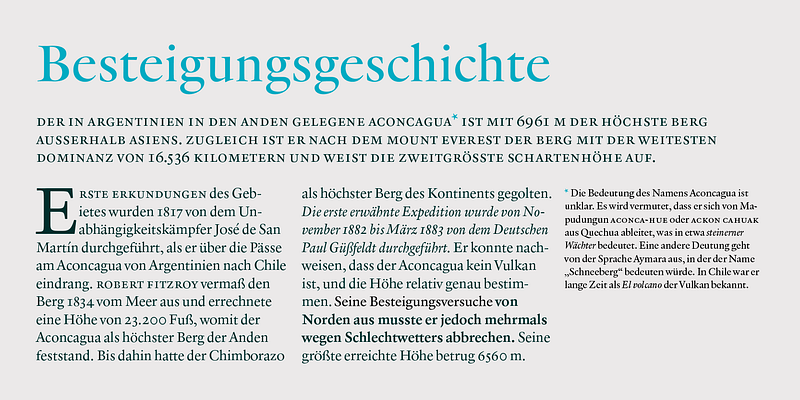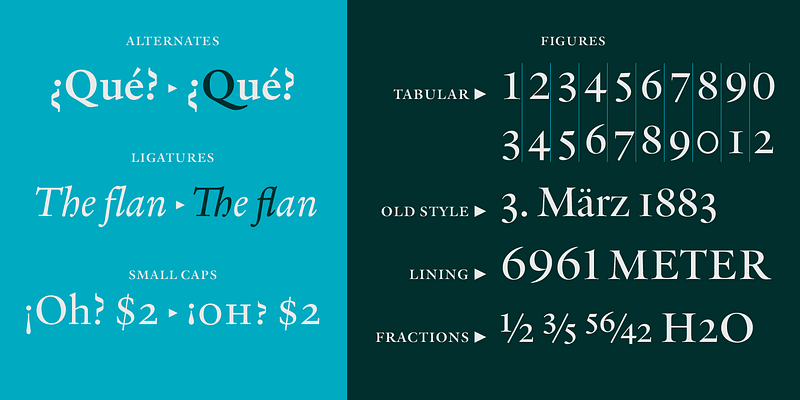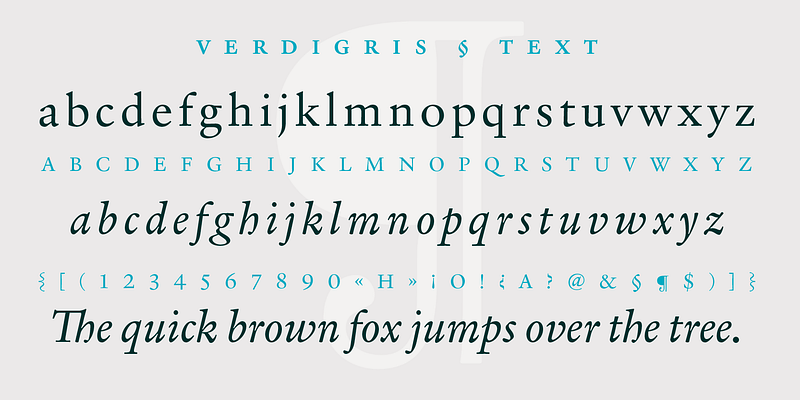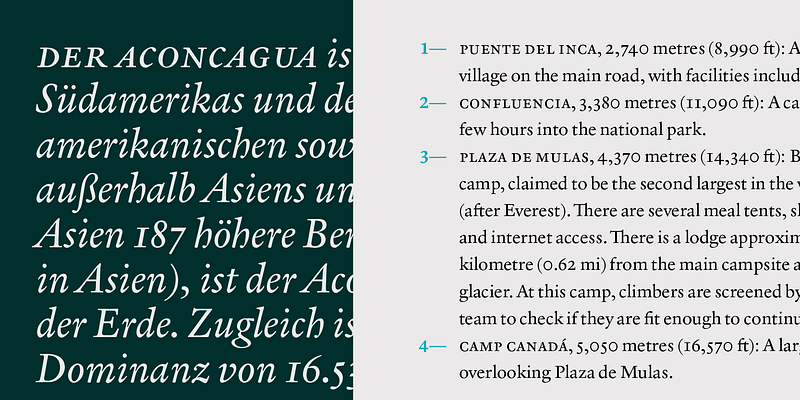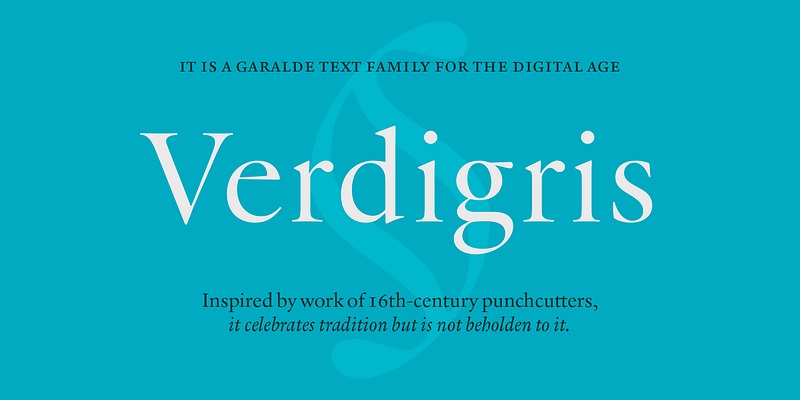
Garalde: Das Wort selbst klingt antik und geheimnisvoll für jeden, der nicht frisch von der Designschule kommt, aber die Art von Schrift, die es beschreibt, ist uns allen eigentlich ziemlich vertraut. Trotz ihres Alters – sie wurde relativ früh in der Geschichte des Drucks geboren – hat sich der Stil gut gehalten; Garaldes sind immer noch die bevorzugte Schrift für Bücher und andere lange Texte. Und so sehen wir auch weiterhin Texte in den alten Favoriten – Garamond, Sabon und ihrem venezianischen Vorgänger, der Bembo. Doch viele neue Bücher fühlen sich nicht so schön und gut lesbar an wie ältere Bücher, die in der ursprünglichen Metallschrift gedruckt wurden. Das Problem besteht darin, dass die Wiederbelebung digitaler Schriften in der Regel Faksimiles ihrer metallischen Vorgänger sind. Sie duplizieren lediglich die Buchstabenformen, anstatt den Eindruck – sowohl physisch als auch emotional – einzufangen, den die Schriften einst auf der Seite hinterließen.
MVB Verdigris ist eine Garalde-Schriftfamilie für das digitale Zeitalter. Inspiriert von der Arbeit der Stempelschneider Robert Granjon, Hendrik van den Keere und Pierre Haultin aus dem 16. Jahrhundert, feiert MVB Verdigris die Tradition, ist ihr aber nicht verpflichtet. Das Design von Mark van Bronkhorst wurde entwickelt, um eine gute typografische Farbe als Text zu liefern, und erfüllt die Anforderungen der Designer von heute, die das Papier und die Druckmaschine von heute verwenden. Die OpenType-Schrift mit vollem Funktionsumfang und einem zusätzlichen ‘Big’-Titelbegleiter ist auch für die neuesten Satztechnologien optimiert.